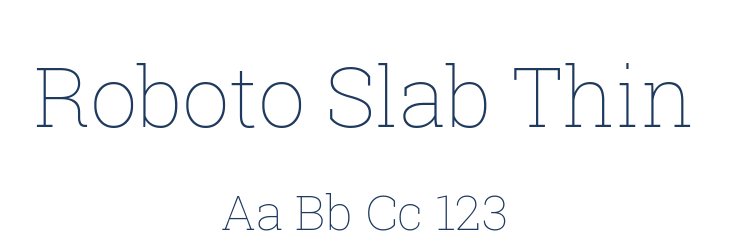
Font family: Roboto Slab
Font subfamily identification: Regular
Unique identifier: Google Roboto Slab 2013
Full font name: Roboto Slab Regular
Postscript font name: RobotoSlab-Regular
Designer: Google
Christian Robertson
Roboto Slab
Regular
Roboto Slab Regular
Новый шрифт Roboto Serif от Google делает чтение более удобным
Автор Кишан ВьясRoboto Serif разработан таким образом, чтобы облегчить работу глаз и обеспечить идеальное качество чтения на экранах различных размеров и при печати.
Google и Commercial Type представили новый изменяемый шрифт под названием Roboto Serif. Шрифт с открытым исходным кодом удобен для глаз и обеспечивает идеальное качество чтения на экранах разных размеров и при печати.
Roboto Serif имеет минималистичный дизайн с «легким шепотом засечек». Шрифт был создан с нуля после множества экспериментов с различными формами и пропорциями, чтобы улучшить его читаемость. Roboto Serif имеет четыре переменные оси и шесть оптических размеров (микро, мелкий текст, текст, колода, дисплей и постер). Вы также можете настроить ширину, высоту, размер и уровень шрифта. Google предоставляет девять готовых версий, включая Thin, ExtraLight, Regular, Medium, Bold и Black.
Roboto Serif — это семейство вариативных шрифтов, предназначенное для создания удобного и удобного чтения.
Минималистичный и очень функциональный, он полезен где угодно (даже для интерфейсов приложений) благодаря обширному набору весов и ширин в широком диапазоне оптических размеров.Roboto Serif — последнее дополнение к суперсемейству Roboto, в которое входят Roboto Sans, Roboto Slab, Roboto Mono и Roboto Condensed. Минималистичный дизайн и универсальность Roboto Serif отличают его от других шрифтов с переменными засечками, таких как Literata, которые предназначены в первую очередь для чтения с экрана. В поддерживаемых браузерах шрифт использует свойство CSS font-optical-sizing, чтобы улучшить качество чтения с экрана. Google говорит, что шрифт остается удобным для чтения в любом размере, в любом формате, от экрана до печати.
«Наша цель состояла в том, чтобы сделать шрифт, который вы могли бы использовать для длинных журналистских материалов или романа — что-то очень длинное и запутанное; захватывающий фрагмент текста, который вы читаете на своем телефоне — не желая жаловаться на это, » сказал Грег Газдович из Коммерческого Типа.